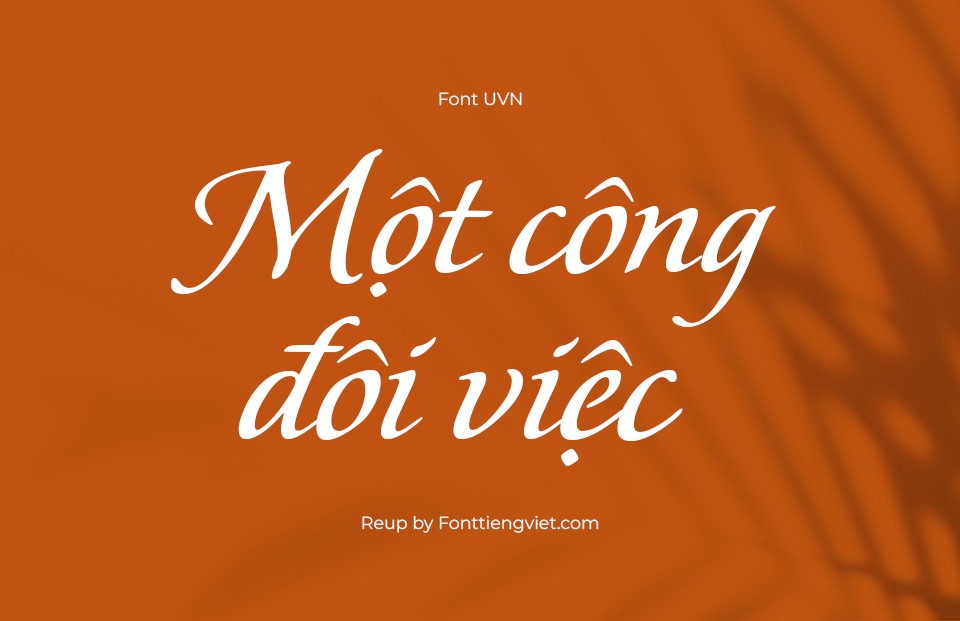
Font Việt Hóa UVN Mau Tim
Giới thiệu về Font Việt Hóa UVN Mau Tim
Trong thế giới thiết kế đồ họa dành cho học đường, việc lựa chọn một bộ Font Miễn Phí phù hợp là yếu tố then chốt để tạo nên sự gần gũi và dễ tiếp thu. Font Việt Hóa UVN Mau Tim là một trong những phông chữ tiêu biểu nằm trong bộ sưu tập UVN nổi tiếng tại Việt Nam. Với nét chữ mềm mại, uyển chuyển và mang đậm phong cách nghệ thuật truyền thống, bộ font này đã trở thành lựa chọn ưu tiên cho các thầy cô giáo và học sinh khi trình bày các bài giảng điện tử hoặc báo tường sinh động.
Đặc điểm nổi bật của Font Việt Hóa UVN Mau Tim
Thiết kế tinh tế và tính ứng dụng cao
Font Việt Hóa UVN Mau Tim sở hữu cấu trúc các ký tự thanh thoát, tạo cảm giác nhẹ nhàng như những nét bút lông. Điểm đặc biệt của phông chữ này là khả năng hiển thị tiếng Việt hoàn hảo, không bị lỗi dấu, giúp văn bản luôn chuyên nghiệp. Với phong cách lãng mạn nhưng vẫn giữ được sự chỉn chu, nó rất phù hợp để làm tiêu đề cho các tập san, thiệp mời sự kiện trường học hoặc các đoạn trích dẫn ý nghĩa trong sách văn học.
Để phát huy tối đa vẻ đẹp của Font Việt Hóa UVN Mau Tim, bạn nên kết hợp nó với các tông màu trung tính hoặc màu tím nhạt đúng như tên gọi của nó. Việc sử dụng font chữ này cho các tiêu đề chính sẽ tạo điểm nhấn thị giác mạnh mẽ, thu hút người xem ngay từ cái nhìn đầu tiên. Hãy đảm bảo bạn tải tệp tin từ nguồn uy tín để có được bảng mã chuẩn nhất. Hy vọng bài viết này giúp bạn tìm được Font Miễn Phí, Font Việt Hóa, Font Việt Hóa UVN Mau Tim ưng ý cho công việc của mình.